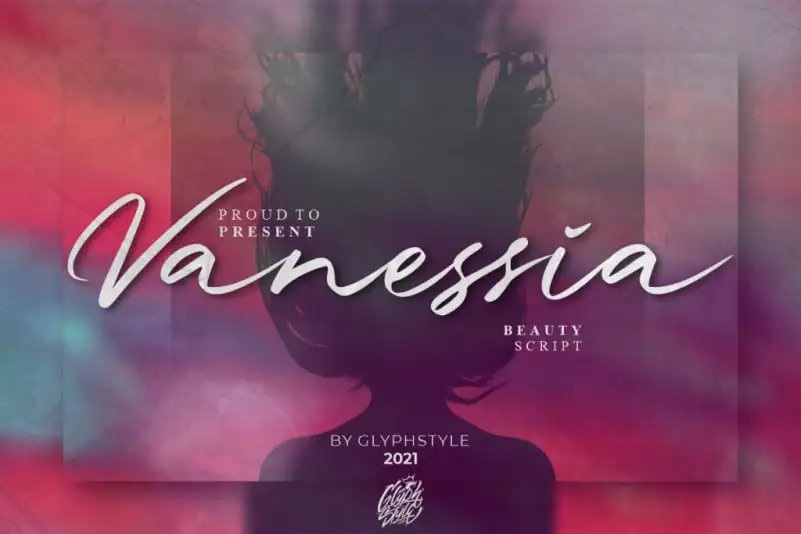
Vanessia Script Font – Download Grátis
A Vanessia Script Font é uma escolha perfeita para aqueles que buscam uma solução elegante e sofisticada sem perder a essência humana e a naturalidade do design manual. Cada caracter é resultado de um truque delicado da mão, transformando-se em uma mistura única de grosso e fino. Esta fonte oferece um estilo naturalmente suave e cheio de irregularidades criadas pelo pincel, tornando-a perfeita para uso em logotipos, selos de água, cartões de visita, marcas de produtos e capas de livros. Desenhada por Glyphstyle no conceito de fontes de esmalte, ela traz uma vibe única que se ajusta perfeitamente a qualquer projeto visual que você possa imaginar. Seja para personalizar um site ou adicionar um toque único à sua próxima publicação, a Vanessia Script é sem dúvida uma escolha inegavelmente encantadora e elegante.